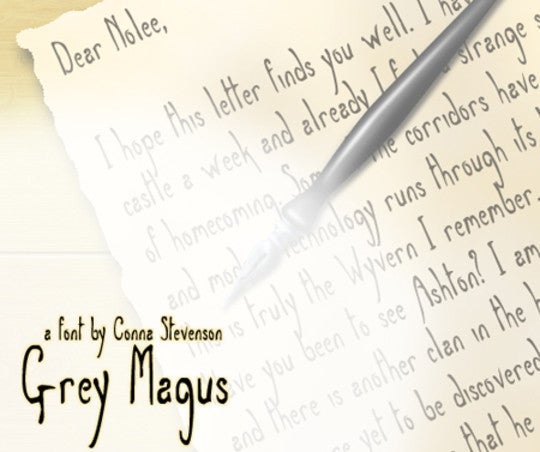
Mit schönen Fonts lassen sich Websites verschönern und vor allem individualisieren. Auffallende Schriften verleihen Webauftritten einen besonderen Reiz. Wir zeigen euch eine Auswahl handgeschriebener Fonts für Webdesigner.
Handgeschriebene Fonts für Webdesigner
Die Website „Smashing Apps“ hat eine Auswahl von 16 handgeschriebenen Fonts zusammengestellt, die Webdesigner für ihre Projekte einsetzen können. In der Auswahl finden sich verschiedenste Schriften: Von solchen Fonts, die aussehen, als wären sie von Schülern geschrieben bis hin zu Comic-ähnlichen Schriften. Durchaus Sinn macht der Einsatz der Schriften beispielsweise in Signaturen – aber auch andere Bereiche der Website profitieren von den markanten Fonts. Im Folgenden eine kleine Auswahl der Sammlung:
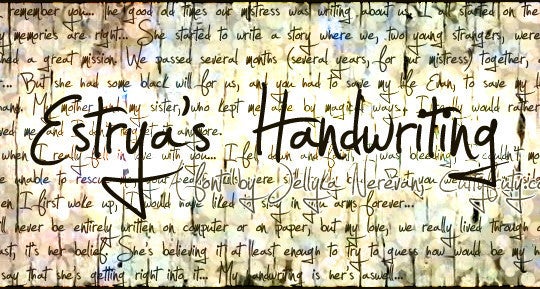
Fonts für Webdesigner: Estray's Handwriting
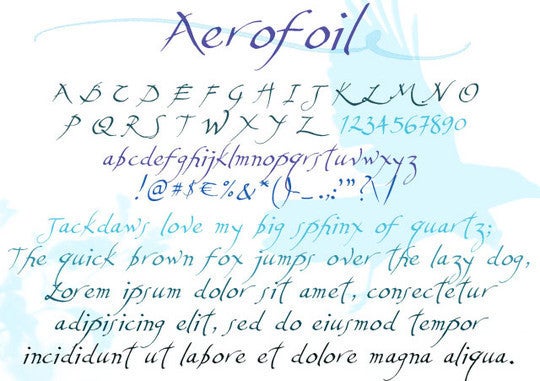
Fonts für Webdesigner: Aerofoil
Die Schrift Grey Magus wirkt recht edel
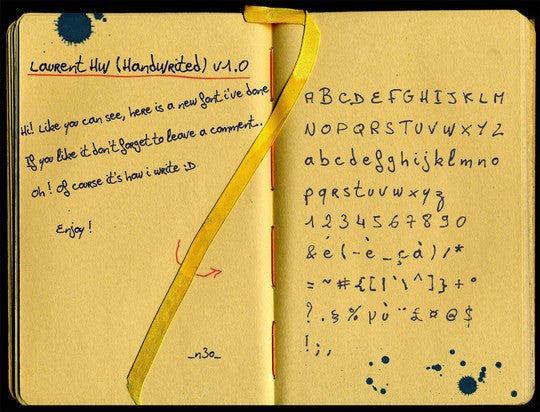
Laurent HW wirkt wie von einem Schüler geschrieben
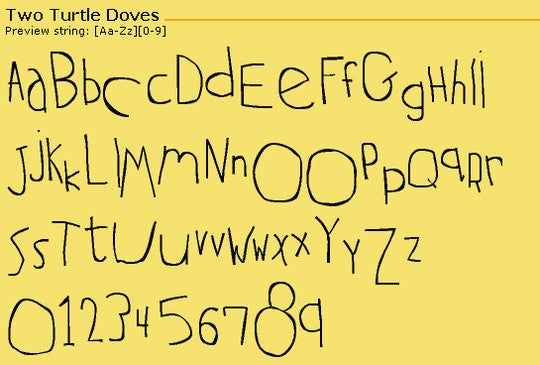
Two Turtle Doves: Eine Kinderschrift